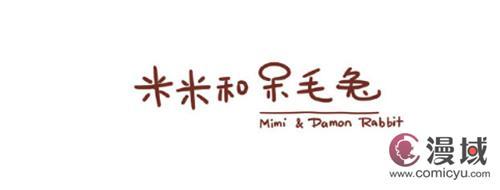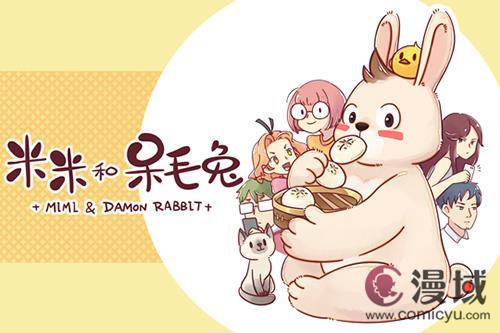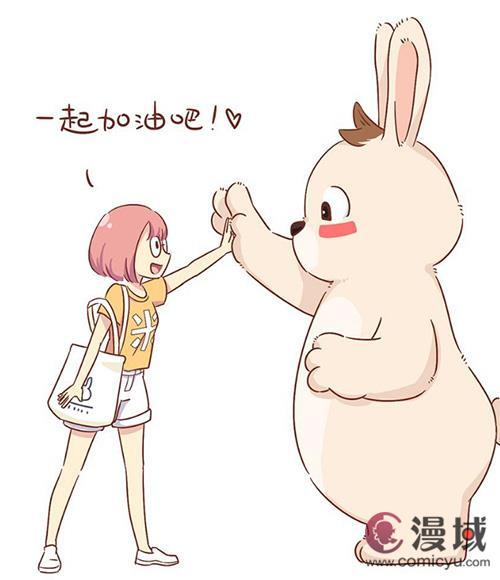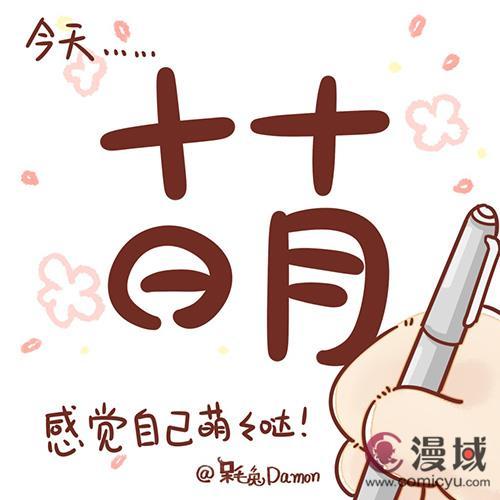
方正手迹携手“呆毛兔Damon”带你穿越漫画世界“呆毛兔字体”软萌上线
方正手迹携手中国动漫形象“呆毛兔Damon”打造呆毛兔软萌体质的专属字体“呆毛兔字体”,以充满趣味性的字形与笔触,让用户在日常生活中随时感受“呆毛兔Damon”带来的暖心陪伴。该字体已于2017年底正式在OPPO、小米、魅族、VIVO等手机商城“萌”动上线。
在与去年备受关注的电影《心理罪》联合推出“心理罪体”、电影《悟空传》同名字体“方正悟空体”,以及热播电视剧《我们的少年时代》同名字体“方正少年时代体”后,方正手迹再次涉猎动漫IP领域,与“呆毛兔Damon”共同为大众提供娱乐性与实用性兼备的“呆毛兔字体”。透过手机终端屏幕,轻松可爱的“呆毛兔Damon”原创字体,让用户拥有“见字如面”的陪伴与感受。
在连载漫画《米米与呆毛兔》中,呆毛兔这只巨大的胖兔来自遥远的外太空中某一颗神秘星球,为了追寻独自在地球旅行的星球公主而来。他并不知道公主的容貌,只幻想着公主是一个善良、懂事、努力、漂亮的完美女孩。一旦发现这样的女孩,他就不由自主的想陪在她身边,在她孤单的时候,静静地陪着她,默默地给她最需要的帮助。
当他遇到米米的时候,一段温馨又带点无厘头的日常生活,就这样展开了。
方正手迹此次携手治愈系漫画《米米与呆毛兔》的作者共同设计打造“呆毛兔字体”,一经推出备受粉丝好评,下载量在很短的时间就已经突破五万。当漫画中的文字跳跃到现实中来,生动有趣的字形透过漫画《米米与呆毛兔》的暖心日常,萌动出世,仿佛真的有一只呆毛兔无时无刻不在你的身边贴心陪伴,带你感受漫画中的趣味情节。
Q萌的“呆毛兔字体”以圆润手写体线条构成字形,简约又不失可爱,既适合日常阅读、书写,又在其中增添了一丝萌趣。以日常使用的手机文字为介质,用呆毛兔Damon漫画同款手写体让你融入《米米与呆毛兔》逗趣横生的奇妙世界。